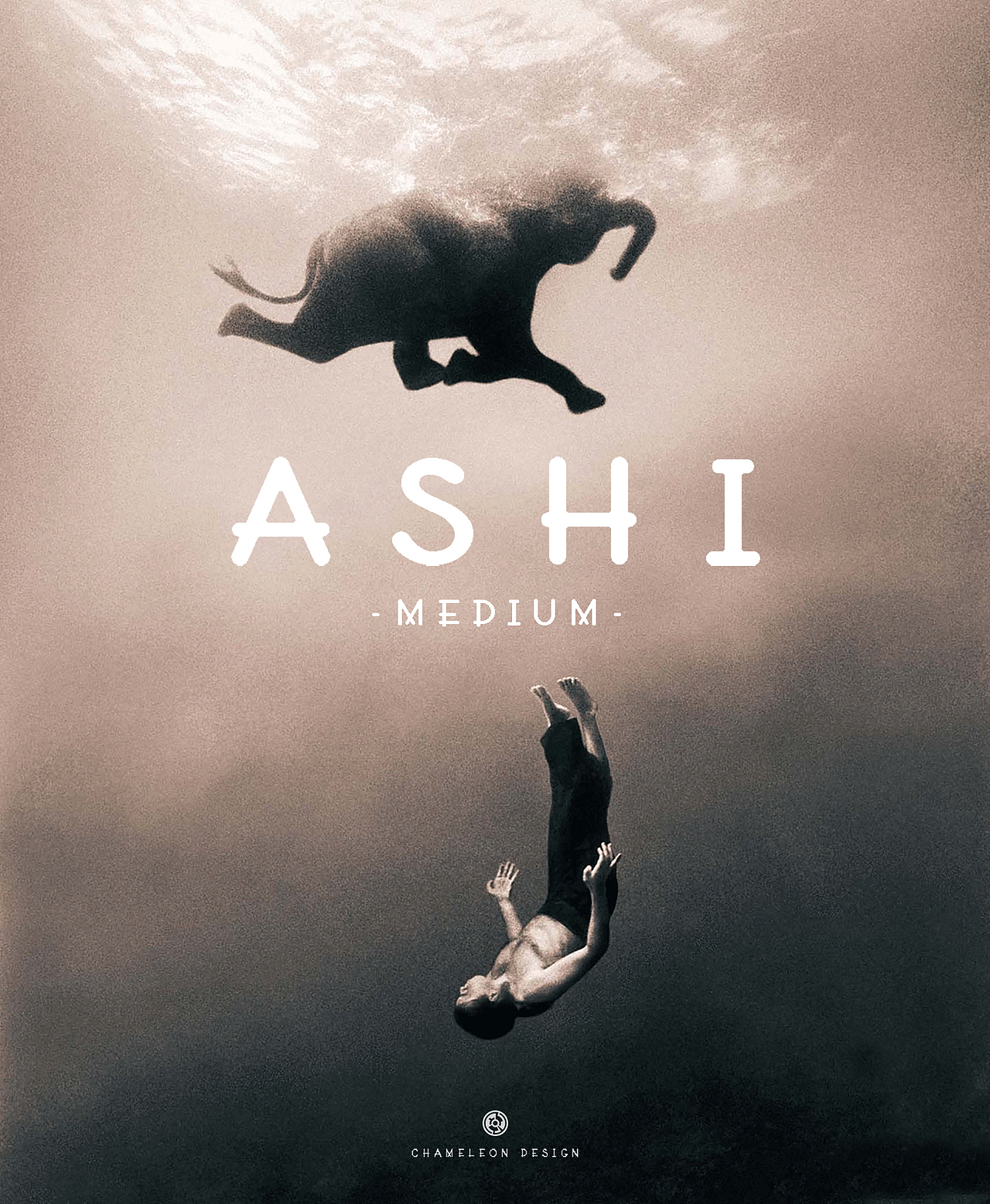
今天刚刚完成 AShi-Medium 版(中粗),放在这里给大家免费下载。之后还会进行修改和调整,放出新的版本。如果大家喜欢的话,还会制做细一些的版本(Regular 常规体)和粗一些的版本 (Bold 粗体)。
受到纪录片 《Helvetica》的启发,我希望做出一款不像 Helvetica 那样中规中矩,有些有趣、独特的变化,又清晰简洁的字体。Helvetica 和与根据它而制做衍生的很多字体如 Arial、Lucida Grande、Futura、Avenir 等等,皆以极简和易读性为目的,尽量去掉字体本身的存在感。我希望尽量保留字体的易读性的同时,再进行简化,然后添加一些特别的变化、让文字看起来更有趣、更生动。而特别的、生动有趣的字体,在取代过于常见的 Helvetica 极其类似的字体的时候,会产生一些有趣的视觉变化,让人们眼前的文字变得不那么乏味,但同时依然较易阅读、并且美观。
AShi 体的特点是极简、独特、有趣、可读,另外一个特点是柔和:所有字母和符号全部细致地使用圆角,让字体在视觉上趋于圆润。AShi 体目前并不完美,有这样那样的缺陷,比如 & 的符号太细、只能和大写字母搭配等等问题,我在修改之后还会推出新的版本喔。
以下字体海报使用了我喜欢的纪录片《尘与雪(Snow & Ashes)》剧照,向伟大的艺术作品致敬。